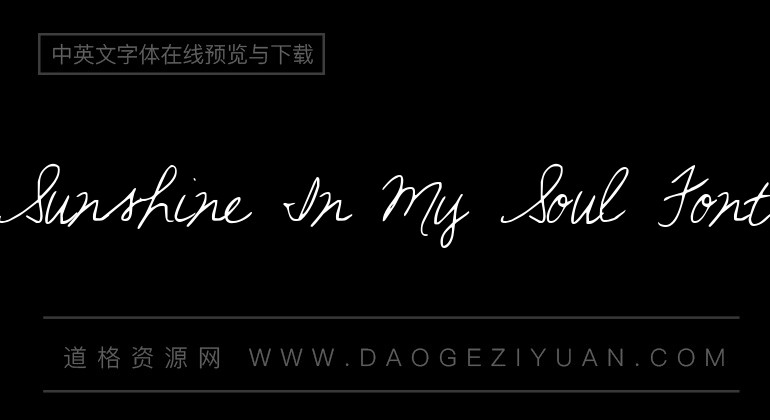
Sunshine In My Soul Font 是一种手写字体,具有轻松、快乐、精神愉悦的感觉。它的特点是字母有点向上倾斜,笔画中也添加了一些装饰元素,例如点、圆弧和花环等,使其看起来更加生动有趣。Sunshine In My Soul Font 适合用于卡片、海报、包装设计、书籍装帧等多种场合,特别适合那些需要传达轻松愉快、积极向上情绪的设计。内容介绍
Sunshine In My Soul Font是一款非常不错的手写艺术字体,具有很好的视觉感,适合于文化类的宣传设计、商业类品牌的广告和产品包装设计以及个性化文字排版等较多场景。